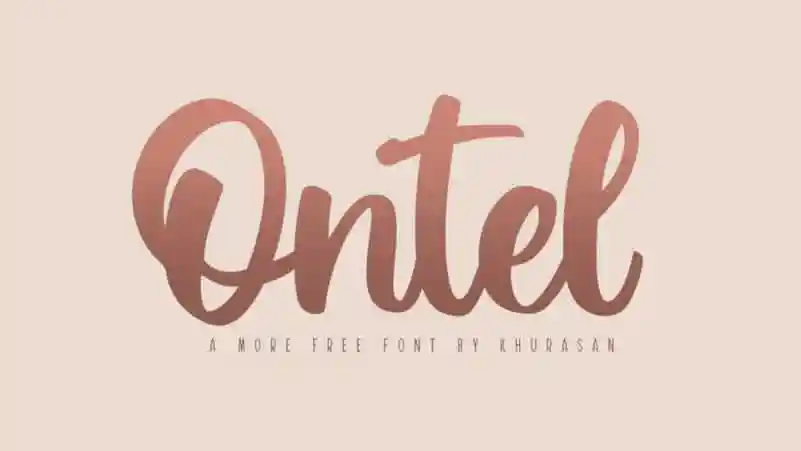
Ontel Script Font é uma elegante tipografia script que transmite autenticidade e simplicidade ao mesmo tempo. Suas curvas suaves e traços delicados criam um ar quase natural, com um toque de mão humana perfeito para qualquer projeto criativo. Idealmente projetado para personalizar elementos de marca ou peças para redes sociais, Ontel Script é uma fonte livre com um charme alegre que se destaca em pacotes de produto, trabalhos manuais e muitos outros usos. Seja em sua composição de texto ou suas imagens gráficas, essa fonte trará um toque único e natural aos seus projetos, proporcionando uma experiência visual autêntica e encantadora.